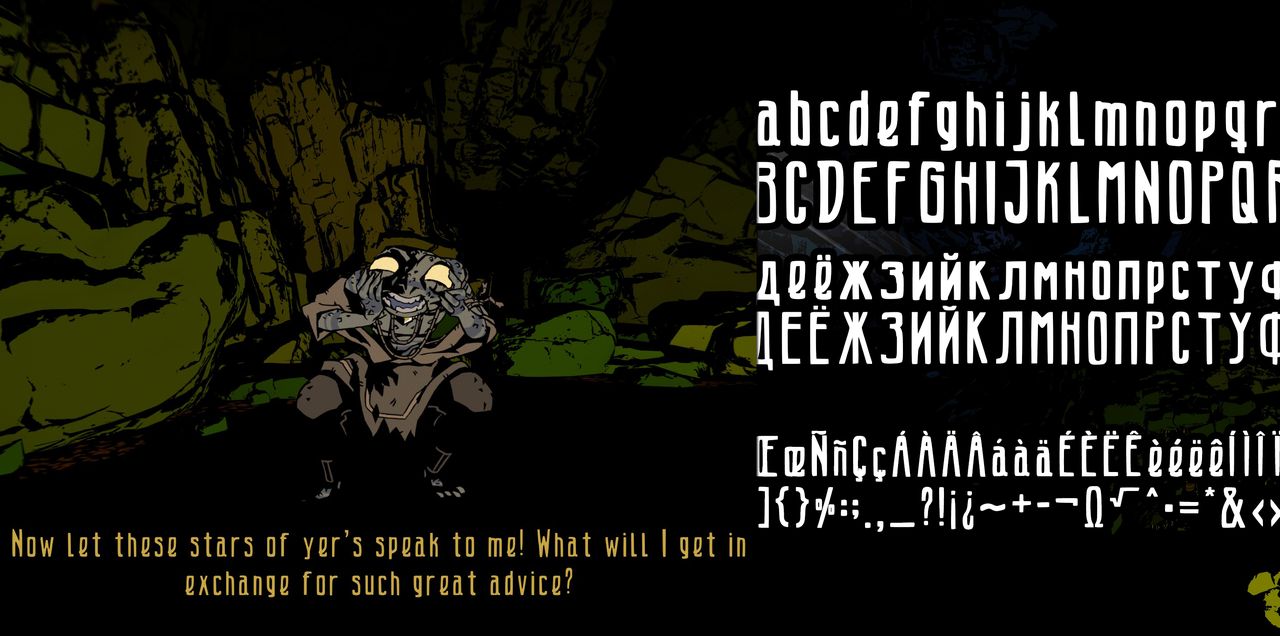
Обновлён шрифт "Like A Cave" от Brainwash Gang
Был обновлён шрифт "Like A Cave" от Brainwash Gang. Это уникальный шрифт, нарисованный от руки и вдохновленный комиксами для использования в играх автора. Шрифт ориентирован на наиболее часто переводимые европейские и русский языки. В новой версии было добавлено ещё несколько символов и букв, а также поддержка украинской локализации, которая становится весьма актуальной.